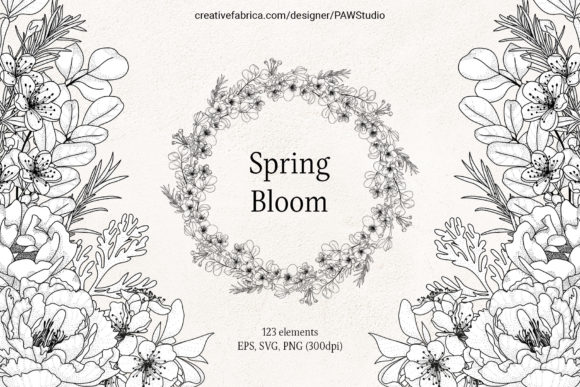
Floral LineArt Flower Frame Monogram
Floral LineArt Flower Frame Monogramのような高品質の素材をお探しの場合、このプレミアムパッケージはクリエイティブなプロジェクトに素晴らしい選択です。
精密に作られたFloral LineArt Flower Frame Monogramは、クリーンなベクター、滑らかなタイポグラフィ、そして安心のための商用ライセンスを提供します。